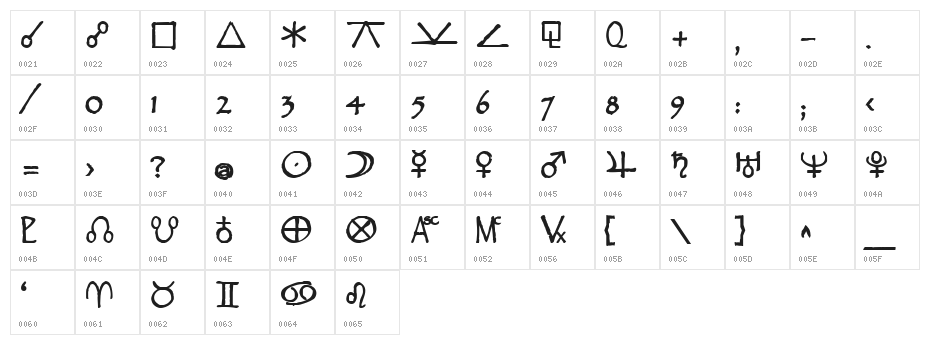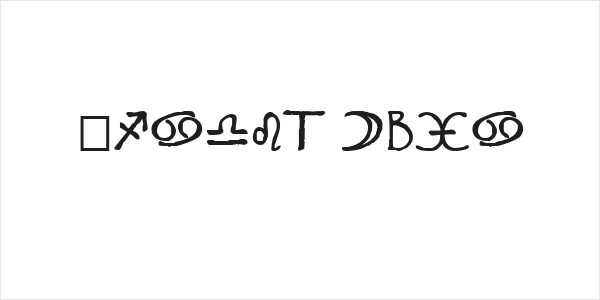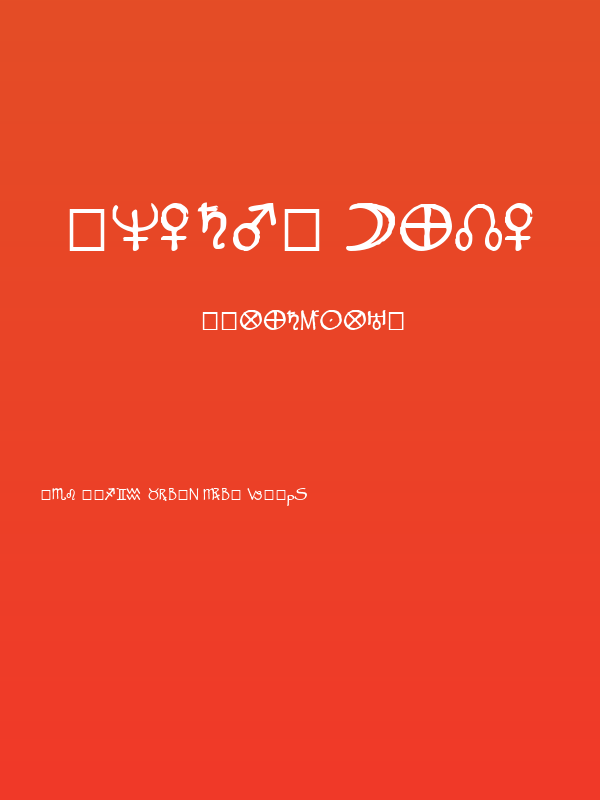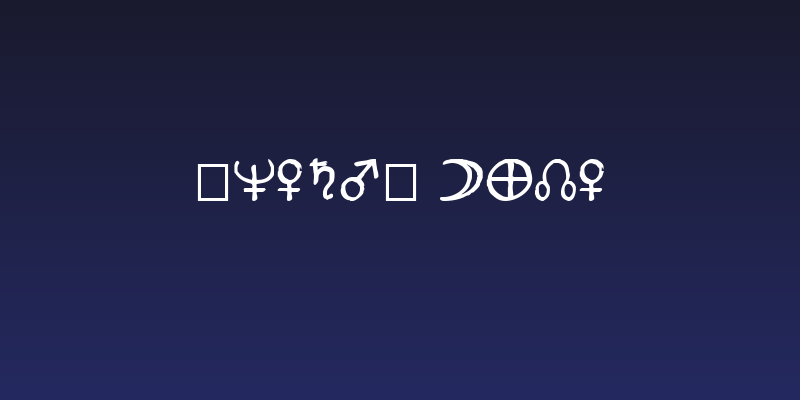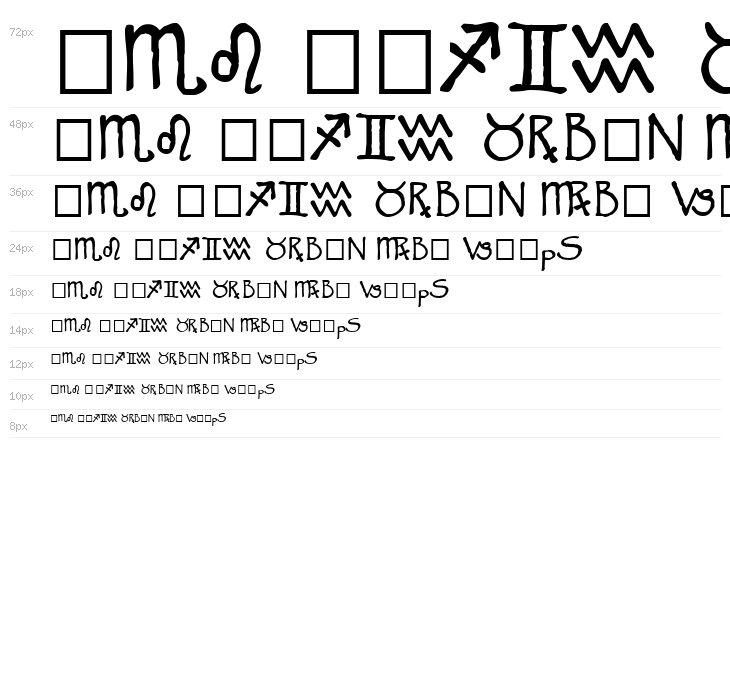
Widget Bold Font
| Style général | Avant-garde |
| Cas d'utilisation | Logos, Artistic projects, Experimental designs |
| Projets proposés | Ideal for artistic projects, experimental designs, and creative branding. |